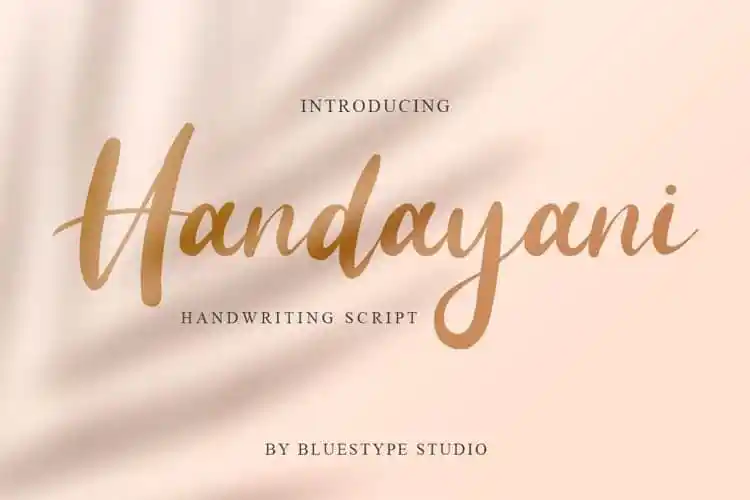
Handayani Bold Script Font – Download Grátis
A Handayani Bold Script Font é uma elegante e moderna seleção de letras cursivas que se destaca no universo das fuentes. Ideal para qualquer tipo de projeto, ela é perfeita para dar um toque único a sua criação. Esta fonte foi criada pela Bluestype Studio e está disponível em 99designs. O diferencial da Handayani Bold Script Font reside na forma bem definida de cada letra, conferindo-lhe um brilho especial que a torna uma obra-prima do design gráfico. Combinando elegância com contemporaneidade, ela é perfeita para diversas aplicações, como design fotográfico, identidades empresariais, decoração de casamentos, criação de t-shirts, logomarcas, publicações, mensagens pessoais e muito mais. Seja você um designer profissional ou iniciante, a Handayani Bold Script Font promete tornar seu trabalho ainda mais impressionante e único, permitindo que você expressa sua visão artística de maneira clara e profunda em qualquer projeto visual que escolha iniciar.